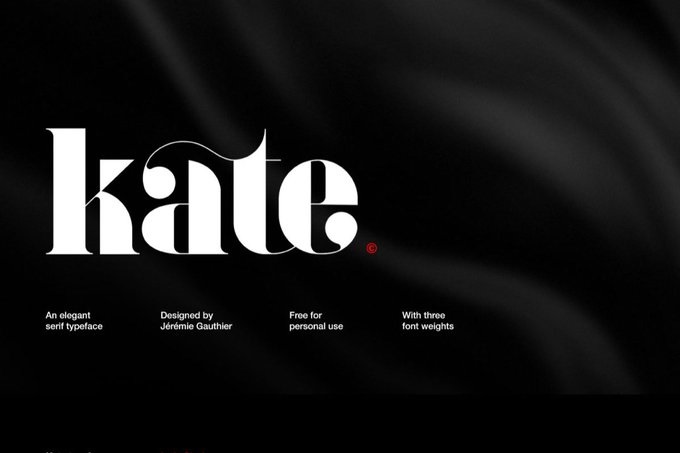
font del giorno: Kate
Kate, di Jérémie Gauthier, è un elegante carattere serif ispirato al mondo del lusso. Il carattere tipografico Kate include 3 pesi di carattere, legature fantastiche, numeri e molte alternative.